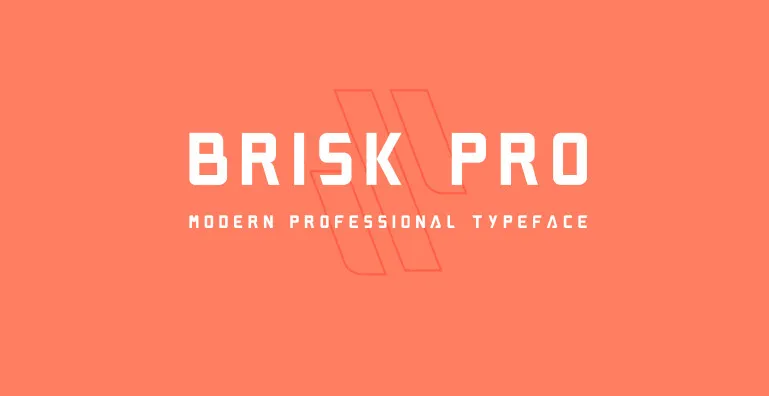
Brisk Pro Typeface – Fonte Grátis
Brisk Pro Typeface
Introduzimos a Brisk Pro Typeface! Desenvolvida por Hamilton, esta fonte sans serif é uma criação gratuita inspirada num logomarca originalmente projetada para um centro de cópias chamado Elva. As letras do Elva foram ampliadas e refinadas para se tornarem uma completa tipografia. A Brisk Pro surgiu como uma nova opção para designers que procuram uma fonte moderna e minimalista, sem detalhes superfluentes. Suave e elegante, esta fonte sans serif é perfeita para criar um design limpo e contemporâneo em projetos de arte digital ou impressão. Ela está disponível gratuitamente com todos os direitos reservados. Se você está à procura de uma nova opção de fonte que seja tanto versátil quanto minimalista, a Brisk Pro pode ser exatamente o que você precisa para seus próximos projetos gráficos.